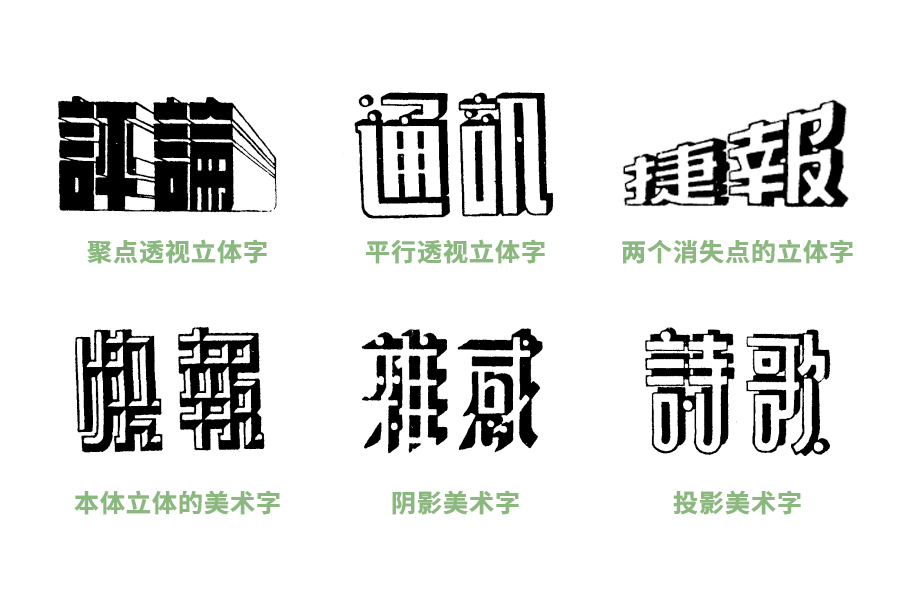
字体百科:「美术字」之「立体美术字」
立体美术字是美术字的一种,它通过特殊的设计和制作技巧,使文字呈现出立体感和空间感。这种字体在设计和艺术领域中广泛应用,能够吸引观众的目光,增强视觉效果。它大致可以分为下面几个类型:聚集点透视的立体字形、平行透视的立体字、两个消失点的立体字、本体立体的美术字、阴影美术字和投影美术字等。